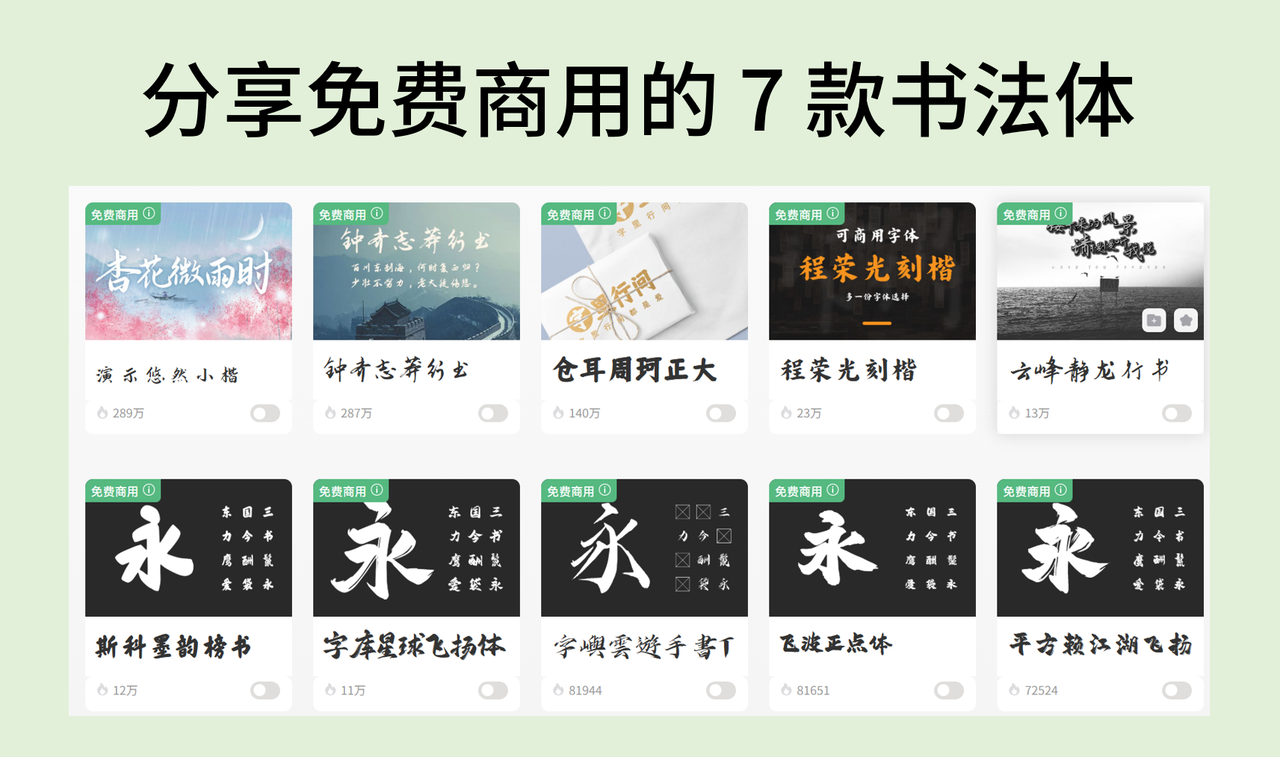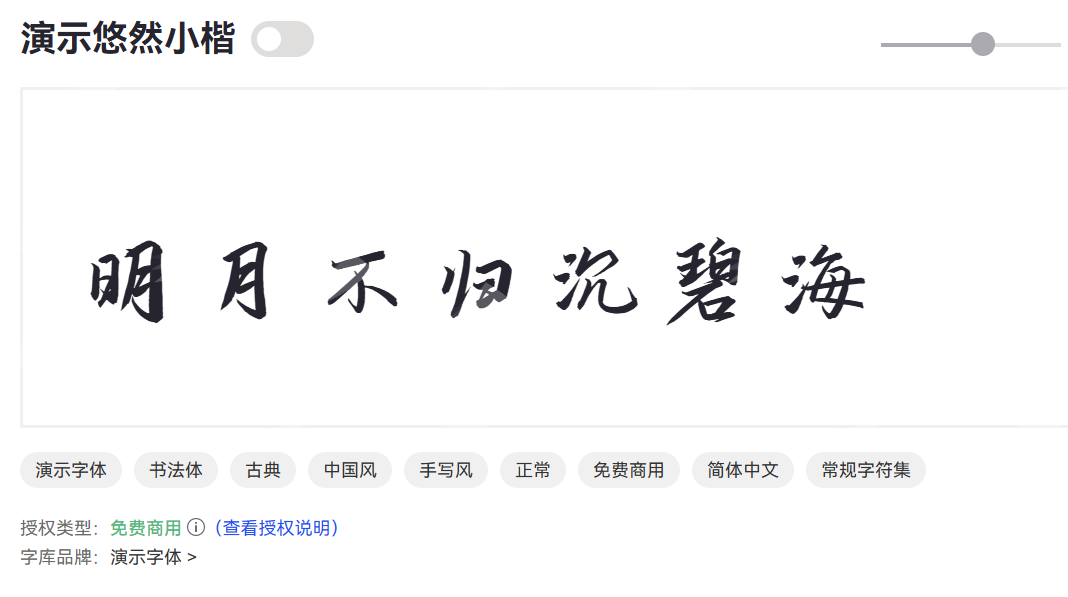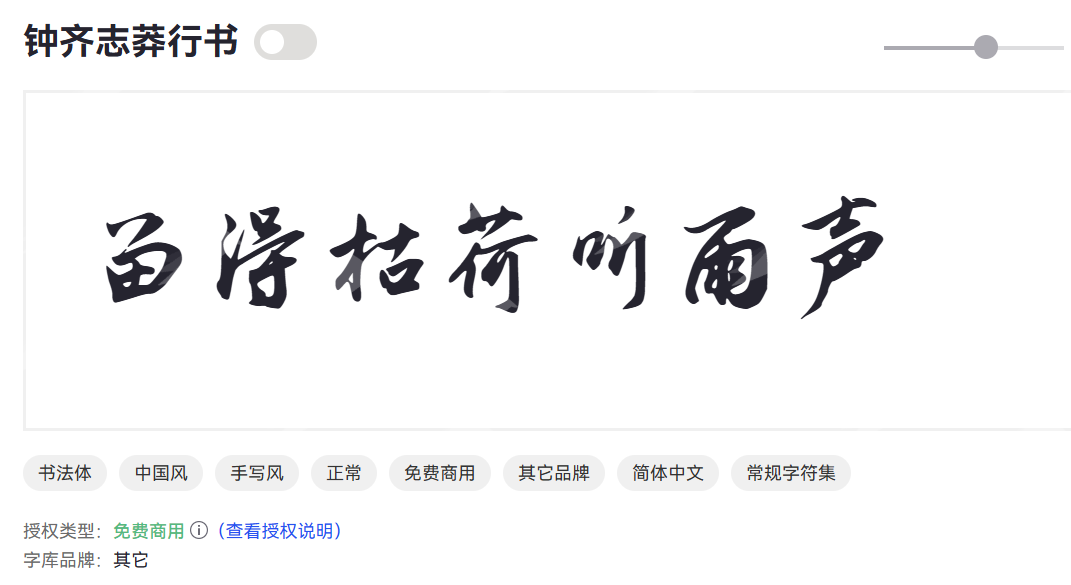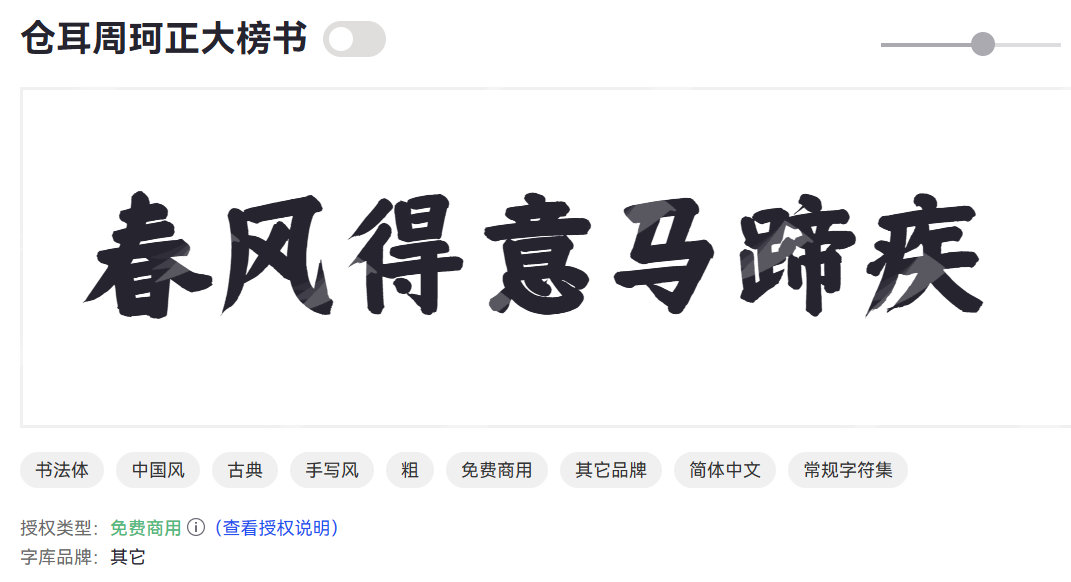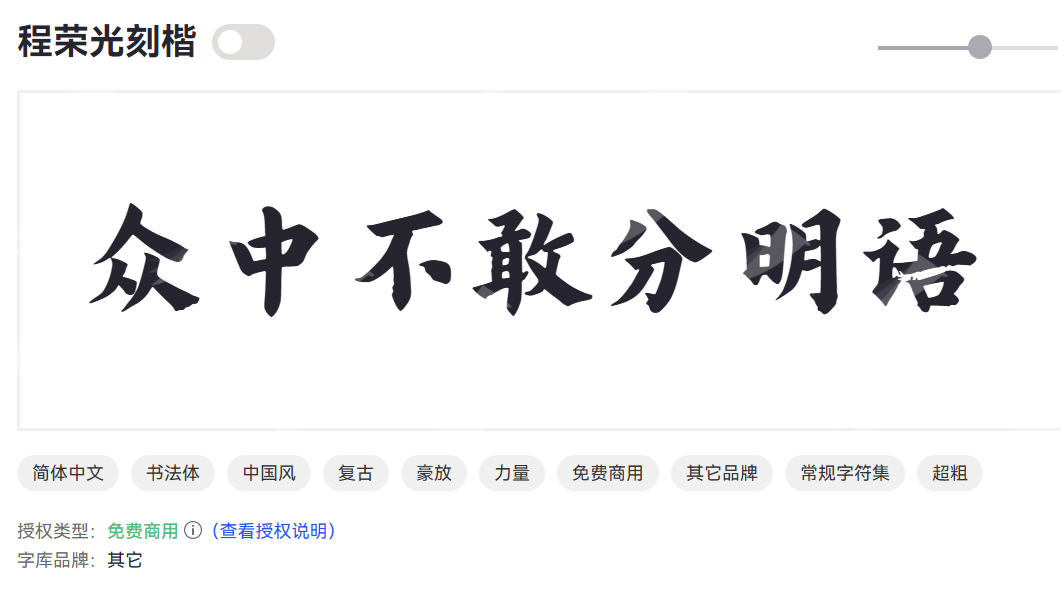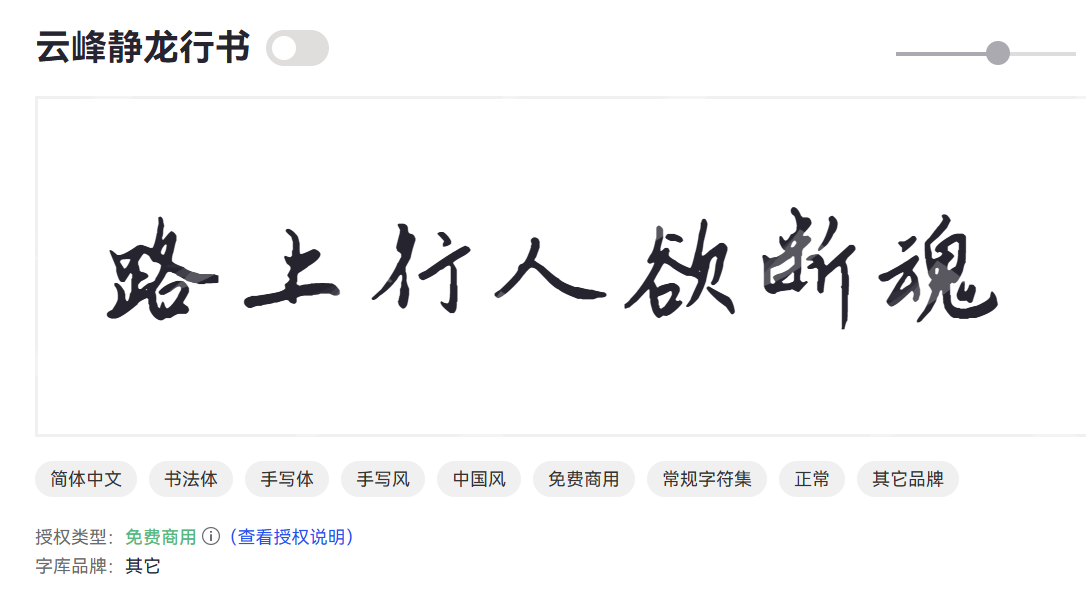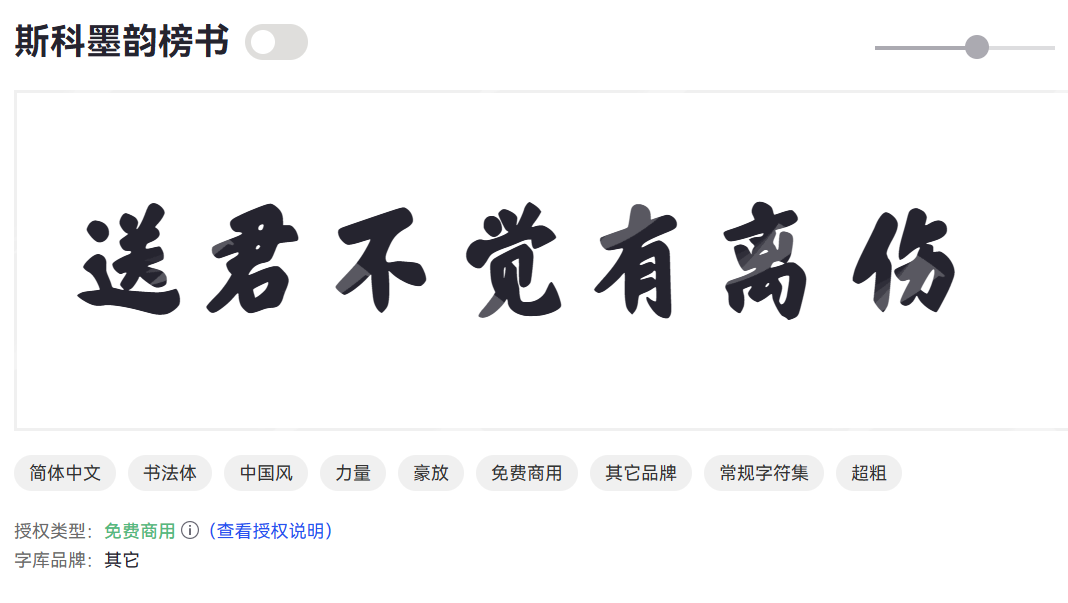
书法体可以商用吗?分享免费商用的 7 款书法体
相信大家在工作和生活中,一定频繁的看到一些书法体的使用,比如当你的目光掠过一张精美的海报,或是翻阅一本古色古香的书籍,那些笔走龙蛇、气韵生动的文字是不是立刻吸引了你的注意?这就是书法体的魅力所在,它不仅仅是一种字体,更是一种文化的传承,一种艺术的表达。
一、 书法体是什么字体?
当我们谈论“书法体”时,我们指的是那些模仿传统书法艺术风格的字体。它将毛笔字、钢笔字、硬笔字等手写体的笔触、结构和神韵,通过数字化技术呈现在我们的屏幕和印刷品上。它不是冰冷的机械文字,而是充满了生命力、节奏感和艺术气息的字体。
书法体最核心的魅力,在于书法文化。它不仅仅是文字的形状,更承载着历史的沉淀、书写者的情感和文化的底蕴。在现代互联网中,将传统书法转化为可用的字体是一项复杂的工程。它需要设计师不仅具备深厚的书法功底,还要精通字体设计软件和技术,才能捕捉到书法的精髓,并将其转化为矢量图形,确保在不同尺寸下的清晰度和美观度。
三、7 款可以免费商用的书法体分享
1、演示悠然小楷
演示悠然小楷是一款典雅细腻的小楷书法字体,笔画细致流畅,结构紧凑均衡,体现了传统小楷的温润与秀逸。演示悠然小楷字体风格稳重且富有书法韵味,适合传递古韵文化和文人气息。
演示悠然小楷线条细腻,笔势自然,具有很强的传统书法艺术感。适合古籍排版、文档书写、文化类出版物及艺术设计。所以使用它能够提升文本的文化品味与艺术感染力。
2、钟齐志莽行书
钟齐志莽行书是一款风格豪放大气的行书字体,笔画流畅且富有力度,线条起伏有致,表现出书法家个性鲜明的书写风格。
钟齐志莽行书笔势豪迈,韵律感强,视觉表现力强烈,表现情感丰富、动感十足的视觉效果。适合艺术展览、品牌形象设计、诗词题字等。我曾经在设计一个艺术展板的标题就用的钟齐志莽行书这款字体。
3、仓耳周珂正大榜书
仓耳周珂正大榜书是一款大气磅礴的榜书字体,笔画厚重有力,结构饱满坚实,充满传统书法的庄重与威严感。
仓耳周珂正大榜书字形宏大,气势雄浑,视觉冲击力强。非常适合用于大型标题、匾额及重要场合书写。适合展览展示、品牌标识、文化遗产宣传等。如果需要一个书法体的标题,我经常想到这款字体。
4、程荣光刻楷
程荣光刻楷是一款严谨规整的刻楷字体,笔画刚劲有力,结构端正清晰,兼具楷书的规范性与刻字的雕刻质感。字体庄重稳健,适合正式文稿与刻字应用。
5、云峰静龙行书
云峰静龙行书是一款灵动飘逸的行书字体,笔势流畅自然,气韵生动,具有强烈的艺术感染力。字体整体轻盈而富有张力,适合表现传统文化与现代审美的结合。
6、斯科墨韵榜书
斯科墨韵榜书是一款具备浓厚书法墨韵的榜书字体,笔画粗壮有力,墨色浓淡变化丰富,展现出传统书法的风骨和气势。适合用于文化展览及高端品牌形象设计。
斯科墨韵榜书墨韵丰富,线条生动,视觉层次感强。适合展览展示、文化活动、品牌LOGO及题字设计。
7、字库星球飞扬体
字库星球飞扬体是一款动感十足的现代书法风格字体,笔画自由流畅,线条轻快飘逸,整体表现出青春活力与创新精神。适合现代创意设计和数字媒体应用。
字库星球飞扬体风格现代,笔触灵动,适合表现创新与活力。适用于广告设计、品牌宣传、数字内容及艺术创作。